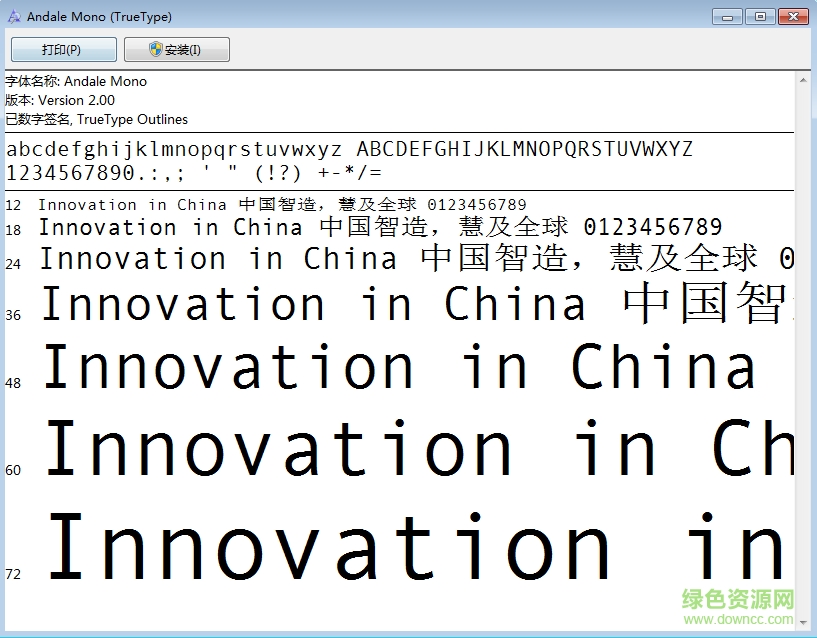
Andale Mono
Andale Mono字體介紹
andale mono字體由于字段固定,字間距較寬,非常適用于程序員編程使用,也可廣泛運(yùn)用于名片設(shè)計(jì)、廣告創(chuàng)意、排版打印等行業(yè)。
andale mono適合于英文輸入,有一定的間距和字寬,讓你的英文書寫更顯干凈整潔,在編程領(lǐng)域使用較廣!